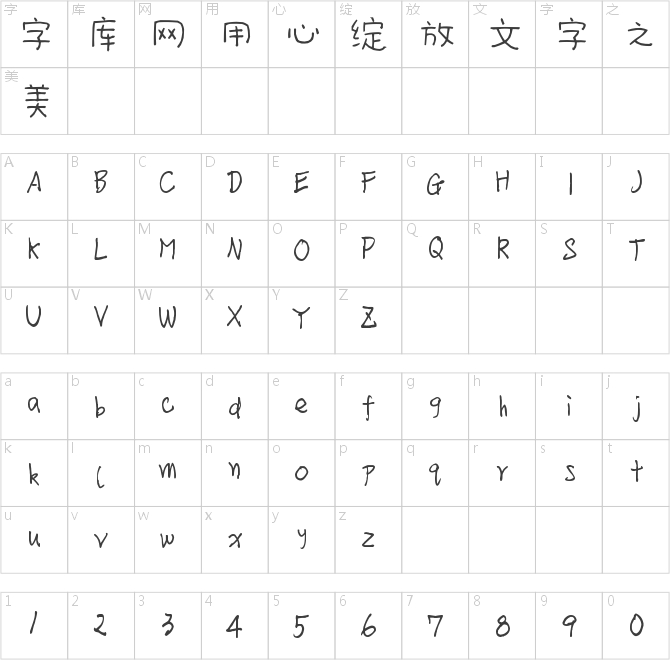
方正泡泡体 详情页
字体名称: 方正泡泡体
一款优秀的字体往往在部件的设计罗辑上是统一的。方正泡泡体的部件设计无疑是优秀的,特别是口、日等封闭部件的处理,具有代表性。另外该字在大小上进得特别设计,使得该字排版看起来活泼、轻快,有一定的韵律与节奏感,就像随风飘舞的泡泡。适用于青少年儿童类、文艺类书刊、漫画综艺字幕、品牌广告和产品包装设计,以及社交网络的个性化用字。